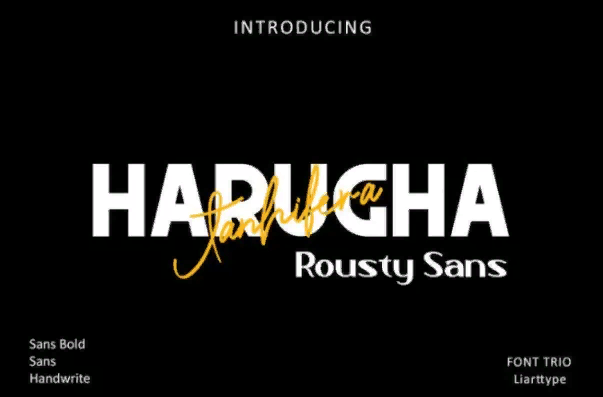
[Fontbundles] Harugha Jhanifera Font (2021)
Название: Harugha Jhanifera Font (2021)
Описание:
Шрифт Harugha Jhanifera Rousty - это трио шрифтов sans, slab bold и handwritte
которые могут помочь вам в создании
модных журналов, логотипов, фотографий, целевых страниц, флаеров,
многоязыковая поддержка